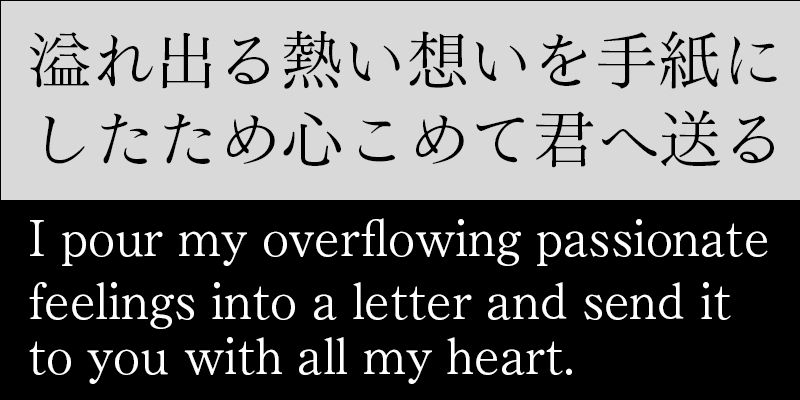
Gli angoli arrotondati dei tratti di Shizuka Mincho rendono questo font ideale per i testi che necessitano di un aspetto visivo più delicato.
TNOF Design ha sviluppato le famiglie di font Shizuka Mincho e Shizuka Gothic ponendo l’accento sulla leggibilità. Shizuka Mincho è pensato per i testi del corpo, mentre Shizuka Gothic, con le sue sei varianti di spessore, può essere utilizzato per un’ampia gamma di usi, dal testo del corpo alle intestazioni.